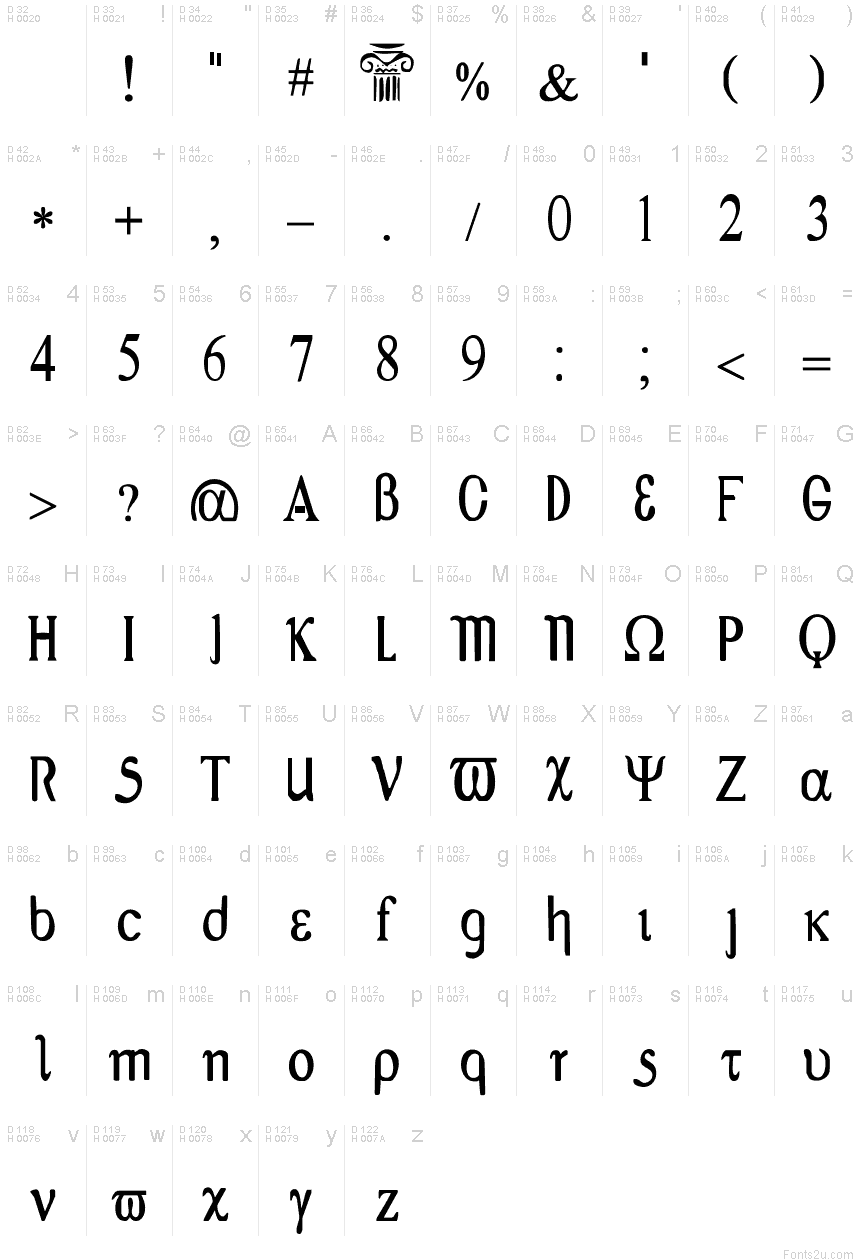
Greex od CybaPeeCreation to darmowy krój pisma z symbolami greckimi, który zmienia klasyczny wygląd «Windows Symbol» w coś cieplejszego i bardziej przystępnego. Dzięki zaokrąglonym kreskom, delikatnym łukom i lekko nieoczywistemu rytmowi, greckie litery przestają przypominać suche notacje, a zaczynają wyglądać jak odręczne napisy, zachowując przy tym czystość i czytelność nawet w małych rozmiarach.
Korzystając z Greex, nadasz spójny grecki charakter ćwiczeniom z matematyki, plakatom naukowym, ulotkom studenckim, publikacjom o tematyce klasycznej, grom edukacyjnym czy zaproszeniom na wydarzenia tematyczne, unikając przy tym sztywnych, podręcznikowych krojów. Ten darmowy font świetnie komponuje się z prostym geometrycznym krojem bezszeryfowym: użyj Greex do treści greckich, a sans-serifu do etykiet w alfabecie łacińskim, aby zachować spójny i czytelny wygląd.
Mapa znaków czcionki Greex